Van een 😑 een 🤩 maken
Inmiddels heeft elke techreus wel z'n eigen brand typeface. Airbnb, Apple, Facebook, Google, IBM, Microsoft, Netflix, Samsung, Uber, Youtube: allemaal hebben ze geïnvesteerd in custom made typografie. Website-template-boer Wix vond het ook tijd worden en lanceert hun eigen Madefor font.
Het voordeel van een brand typeface is dat het karakter ervan precies kan aansluiten op wat je als merk wil uitstralen. Een uitstekende kans om je eigen merkpersonaliteit te uiten. Een kans die Wix volledig laat liggen. Hun Madefor (gemaakt door typefoundry Dalton Maag) is een prima ontworpen, maar generiek lettertype met de uitstraling van een Opel Astra.
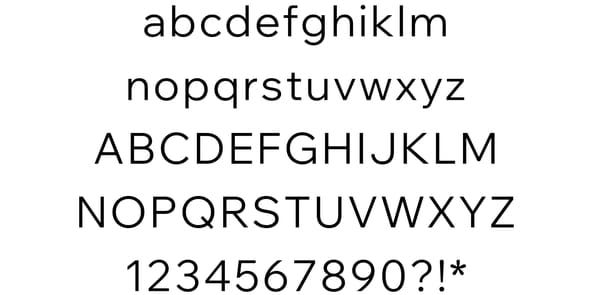
Bij Wix denken ze daar anders over. In hun ogen barst het font van personaliteit en unieke eigenschappen:
“We take a lot of pride in our in-house multidisciplinary design studio, and we noticed the brand was missing a critical element of design, a custom and easily recognisable typeface. We set out to create a bespoke typeface that was distinguishable and represented our brand values.”
Easily recognisable? Really?!
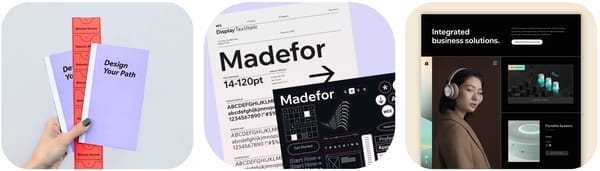
En check de lanceervideo, die laat zien dat alle karakter, eigenheid en juice zit in de toepassing van het lettertype, niet in het font zelf:
Ik moet steeds denken aan dat ene sprookje, iets met de kleren van een keizer 🤔
Must use
Daisydisk – Werken met Dropbox selective sync, een beperkte hardeschijfruimte en gigantische projectmappen is vaak een hel. Daisydisk geeft je een perfect overzicht van je harde schijf waardoor je makkelijk erachter komt hoe je ruimte vrijspeelt. Ik kan niet meer zonder.
FRESH FONTS
LiebeHeide (LiebeFonts)
Eklektyk (Laïc: Type Foundry)
New Forest (Beasts of England)
TOOLS
De schaduwkant van HalfVet
Synthesia laat je tekst uitspreken door een AI-gegenereerde presentator in een te downloaden video.
The Accessibility Resources is een enorme verzameling plugins, tools, artikelen, technieken en standaarden rond accessibility.